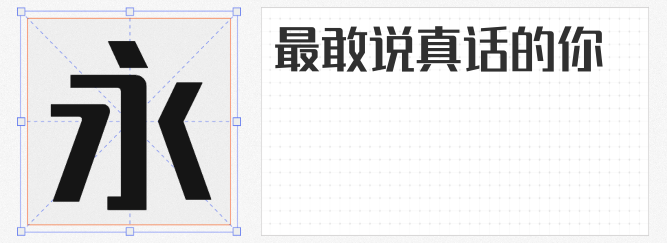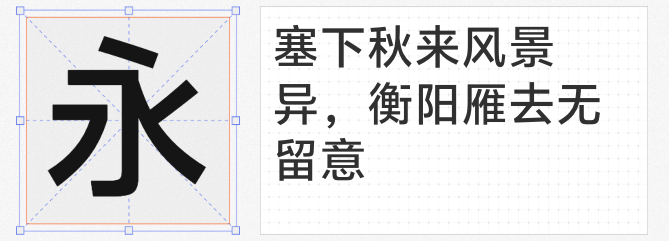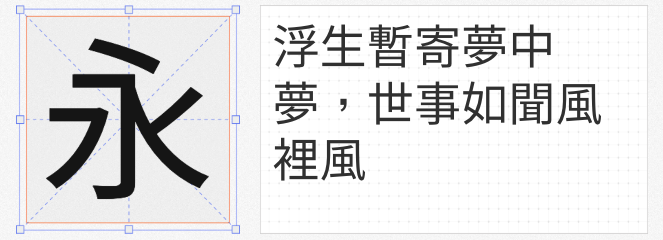
黑体字体以其简洁现代的骨架、清晰的视觉层次和强烈的视觉冲击力,始终是设计领域的“万能选手”。无论是品牌标识、海报标题还是数字界面,一款优秀的黑体字体既能传递力量感,又能保证信息的高效传达。以下四款免费商用黑体字库,以其独特美学与实用性,为设计师提供多元选择:
这款字体以“直角与圆角的错落搭配”形成独特韵律,笔触浑厚而不失灵动。其笔画转折处的圆润处理削弱了黑体常见的生硬感,在力量感与亲和力之间找到平衡。适合潮流品牌、音乐海报或需要彰显个性的场景,既能突出标题的醒目效果,又能避免视觉疲劳。
脱胎于“未来荧黑”的基因改造,这款字体通过横向减细、纵向增粗的调整,赋予其介于科技感与人文气质之间的独特气质。优化后的数字“4”“7”及字母“K”“k”修正了原字体的比例问题,使其在屏幕与印刷场景中均表现稳定。适合科技产品、文化展览或需要现代感与传统韵味并存的设计。
由知名手机品牌vivo推出的这款字体,彻底贯彻“去装饰化”理念。其笔画末端采用独特的切角设计,既保留黑体的骨架清晰,又通过灰度优化提升长时间阅读的舒适性。在APP界面、电子书或信息图表中表现尤为出色,是功能与美学平衡的典范。
以思源黑体与宋体KR版为基底,台北黑体对“旧字形”进行当代化改良,既保留传统印刷字体的韵味,又符合现代屏幕显示需求。其笔画细节处的微调(如“口”字结构的微调)使其在标题与正文切换时依然保持高度统一,尤其适合传统文化类项目或需要兼顾怀旧与创新的场景。
这四款字体不仅覆盖从力量感表达、科技美学到极简阅读的多元需求,更重要的是其免费商用的属性(需遵循各字库的具体授权协议)大幅降低了创作成本。它们证明:优秀字体不一定是昂贵的代名词,而是设计师用创意突破工具限制的伙伴。尝试将它们融入你的设计流程,或许会发现新的灵感维度。